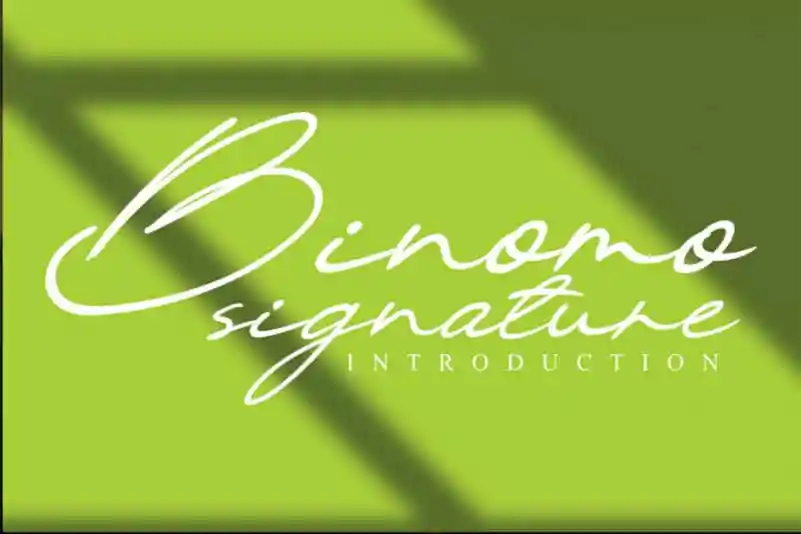
Binomo Handwritten Font – Fonte Grátis
Binomo Handwritten Font
Binomo Handwritten Font é uma fonte inspirada no tipo clássico que traz seu próprio estilo único para qualquer projeto de design. Inspirado por influências do calligrafismo, esta fonte mantém seus elementos sofisticados ao mesmo tempo que parece contemporânea e fresca. Esta versatilidade a torna ideal para ideias criativas em diversos aplicativos, desde cartões de correspondência até assinaturas e materiais de escritório. Seja você um designer atento aos detalhes ou um artesão buscando uma fonte única que traduz seu estilo pessoal, Binomo Handwritten Font é a escolha certa para iluminar seus projetos com seu próprio toque personalizado.